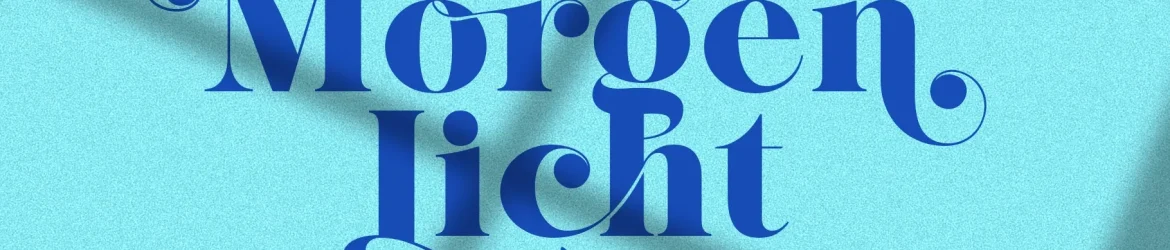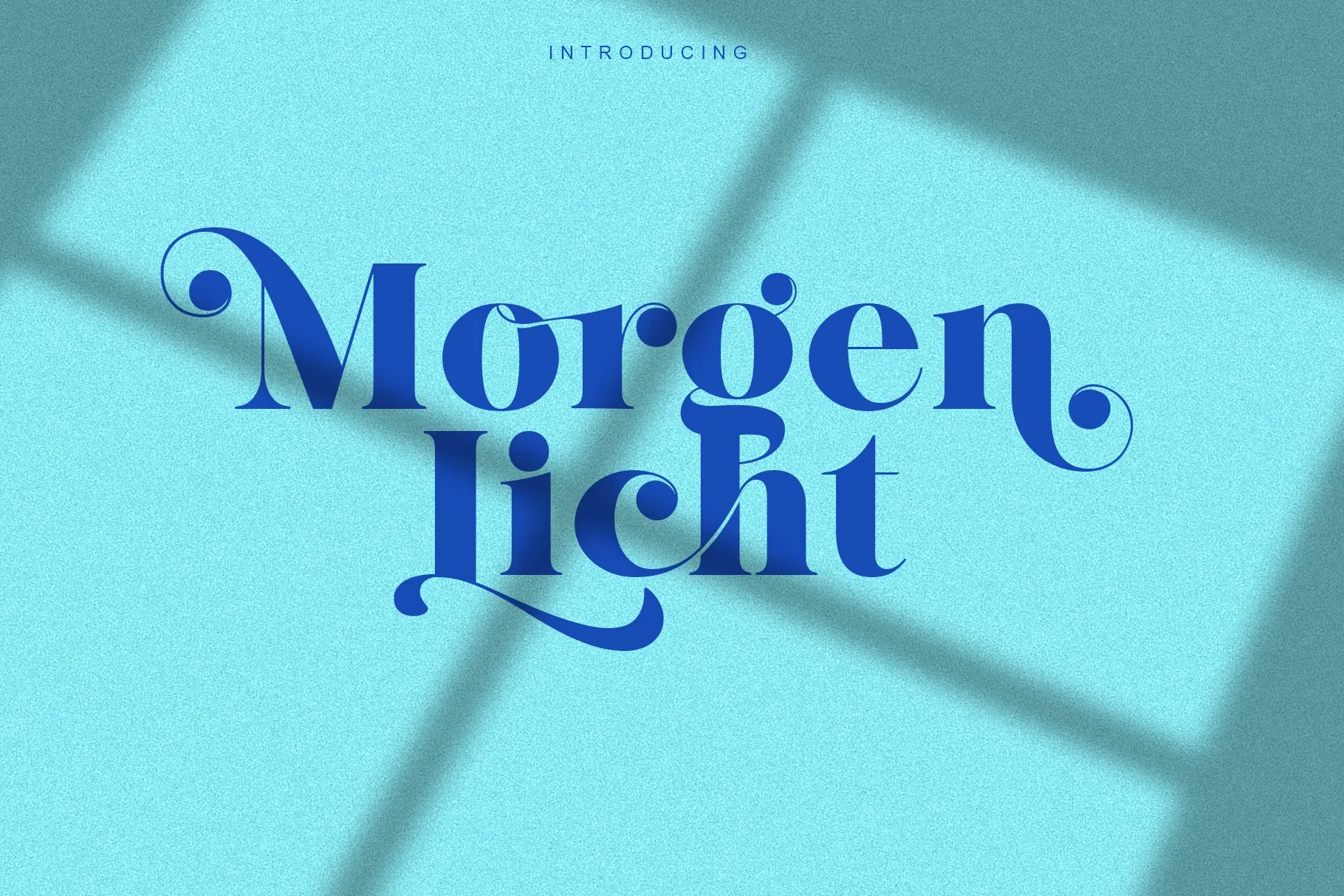
Morgenlicht Font
A fonte Morgenlicht é uma elegante serif que transmite um ar romântico em cada curva de letra. Inspirada na cultura do leite d’água alemão, essa tipografia moderna foi cuidadosamente criada e compartilhada pelo designer handpik. Ideal para cartões de convites, decorações, roupas, cartas de cumprimento ou qualquer outra aplicação visual onde uma fonte serif seja desejada. Com letras maiúsculas e minúsculas inclusas, a Morgenlicht é também capaz de abranger números e pontuação. Além disso, oferece várias ligaturas e alterações estilísticas que adicionam mais um toque ao seu design gráfico ou publicitário. Seja para expressar uma paixão única em cartões de casamento ou transformar uma camiseta em peça de arte perfeita, a Morgenlicht é uma escolha inegável para designers e criadores de conteúdo.